밑줄 긋는 디자이너.18_<비오는 날 읽는 그래픽 디자인의 역사>
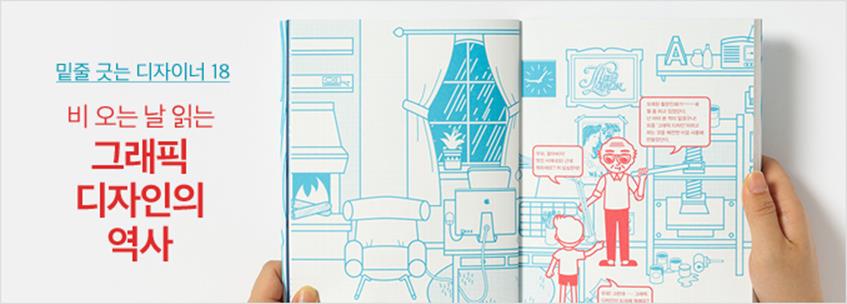
비 오는 날 할아버지 집에 놀러 갔다가 ‘그래픽 디자인이 뭐예요?’라는 질문에서 시작된 하룻밤의 디자인 역사 여행이 이 책의 큰 구조로 이루어져 있다. 산업혁명 초기에 이루어진 타이포그래피의 미약한 탄생부터 오늘날 인터넷을 중심으로 하는 글꼴의 유통까지.
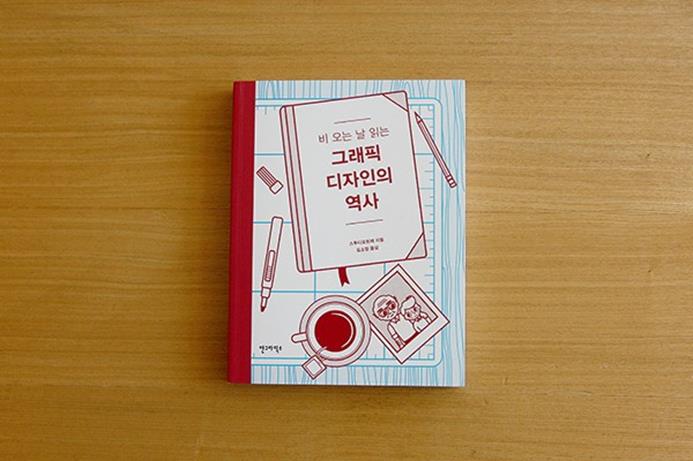
크리스마스카드를 처음 만든 사람은 누구일까?
다다의 이름은 어디에서 유래했을까?
최초로 CI를 만든 사람은 누구일까?
색상환은 누가 만들었을까?
푸투라, 유니버설, 길산스, 사봉 등 글꼴은 어떻게 만들어졌을까?
현재 우리가 쓰는 지하철 노선도의 형태를 가장 처음 만든 사람은 누구일까?
하룻밤의 디자인 역사 여행
페이지마다 두 가지 색상으로 이루어진 그래픽 일러스트레이션과 쉬워 보이는 화면구성에 이끌려 이번 기회에 머릿속에서 희미해진 디자인 역사를 가볍게 정리하자는 생각으로 이 책을 들었다.
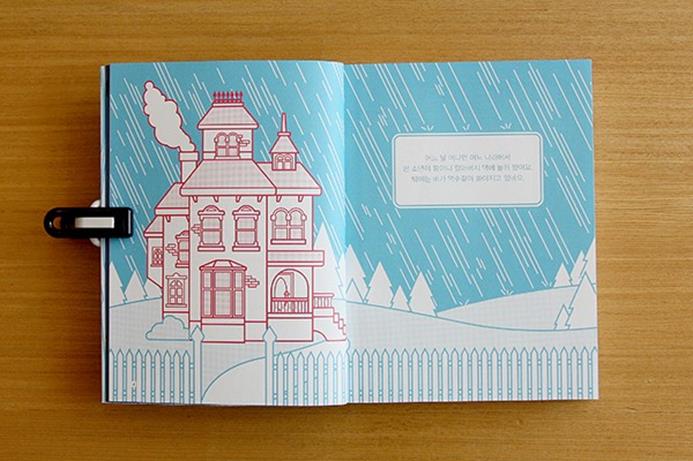
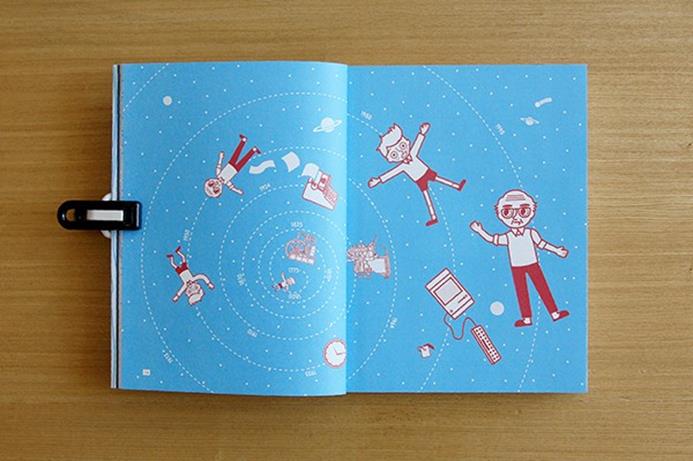
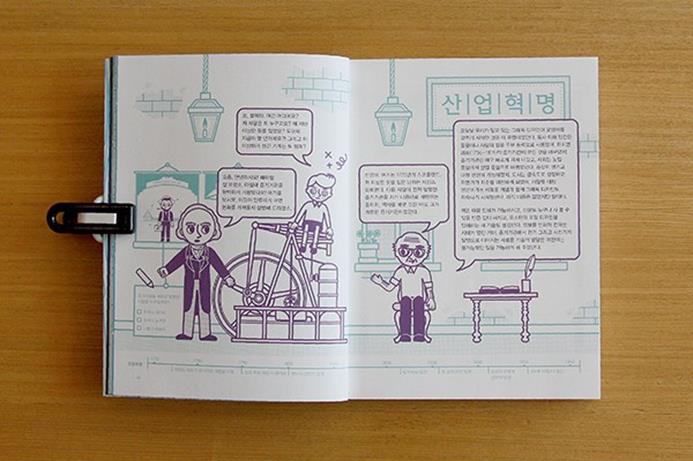
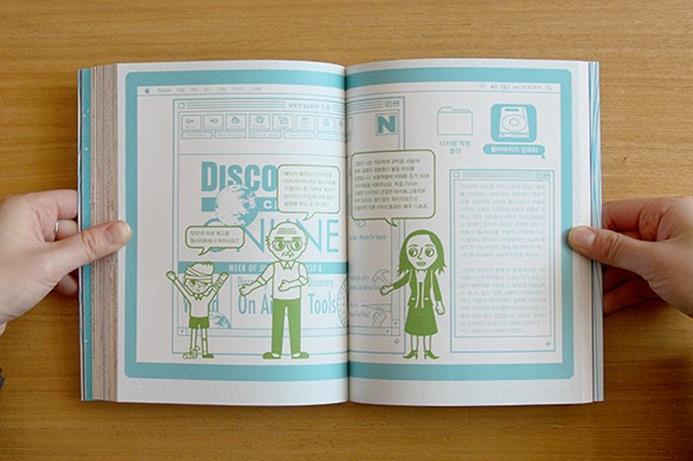
비 오는 날 할아버지 집에 놀러 갔다가 ‘그래픽 디자인이 뭐예요?’라는 질문에서 시작된 하룻밤의 디자인 역사 여행이 이 책의 큰 구조로 이루어져 있다. 산업혁명 초기에 이루어진 타이포그래피의 미약한 탄생부터 오늘날 인터넷을 중심으로 하는 글꼴의 유통까지. 아르누보, 미래주의, 다다 운동, 러시아 구성주의, 바우하우스 등 시대별, 연대별로 그래픽 디자인의 특징을 일별하며 그래픽 디자인 세계에서 일어난 굵직한 사건들과 오언 존스, 알폰스 무하, 윌리엄 브래들리, 앙리 반 데 벨데, 엘 리시츠키 등 쟁쟁한 대가들을 찾아간다. 그 과정에서 그래픽 디자인과 관련된 궁금증을 하나둘씩 풀어낸다.
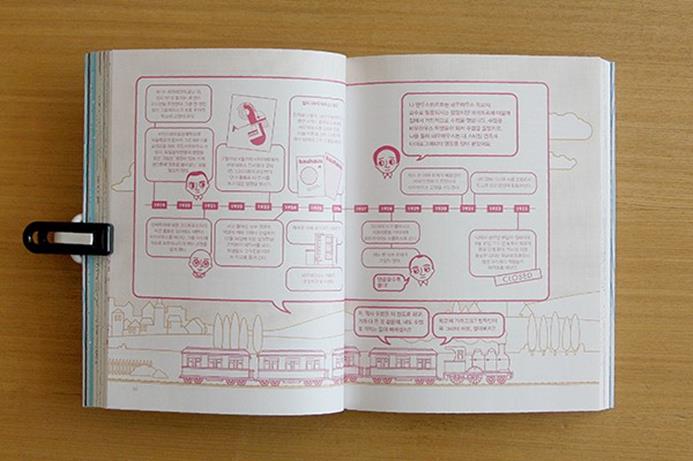
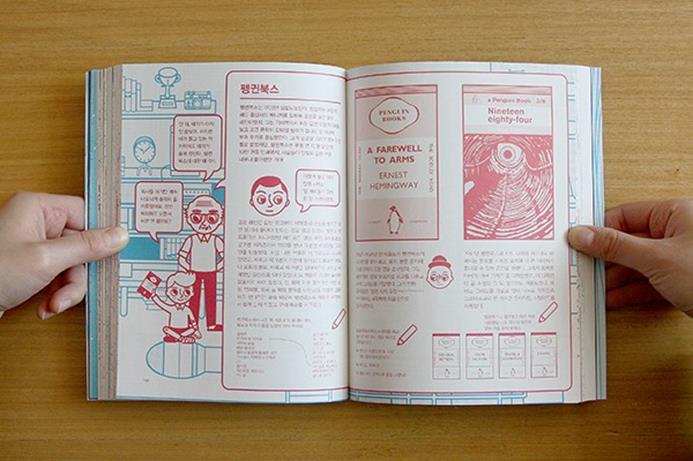
신문과 잡지부터 책 표지, 상품 라벨, 포장지, 각종 글꼴이나 기업체 로고, 포스터, 음반 재킷,웹사이트, 심지어 영화 타이틀 시퀀스까지.
그래픽 디자인의 역사의 사건과 그 시대에 굵직굵직한 역사의 흐름도 함께 알려주어 더 큰 흐름을 이해하는 데 도움을 준다.
P.78-79
바우하우스 1919-1933
-바우하우스라고 들어 오셨나요? 요즘엔 독일 어디를 가도 그 이름을 들을 수 있더군요. 그 학교에 피닝거라는 사람과 이야기를 나눠 보니 디자인이나 미술에 대해 나와 비슷한 생각을 하고 있더라고요. 바이마르에 바우하우스가 있는데, 그곳에서 가르치게 되기를 바라고 있습니다.
-그럼요, 들어봤지요. 디자인 전반, 특히 그래픽 디자인 분야에서는 짧지만 강렬한 흔적을 남긴 곳이니까요. 바우하우스의 철학을 형성하는 데 수많은 사람들이 힘을 보탰고 서로 다른 세 곳의 학교가 새로운 현대 디자인 운동의 중심이 되었지요. 또 바우하우스는 진정한 디자인 교육 환경을 만들려는 첫 시도이기도 했답니다.
-바우하우스의 학생들은 도예와 건축, 그리고 사진에 이르기까지 수많은 기술을 익혀야 했답니다. 오른쪽의 표는 학생들이 공부한 여러 과목을 잘 보여 주고 있지요. 바우하우스 교육 과정…생략
1918 – 제1차 세계대전 종전
1920 – 최초의 라디오 광고가 전파를 탐
1922 – 독일의 심각한 인플레이션
1924 – 유성 영화 발명
1926 – 레닌사망
1928 – BBC설립
1930 – 주가 폭락, 대공황
1932 – 엠파이어 스테이트 빌딩 완성
1934 – 아돌프 힘틀러가 독실 수상이 됨
1936 – 나치 독일에서 올림픽 개최
간단한 퀴즈와 직접 오릴 수 있는 부록까지 곁들여 디자인의 세계를 경험할 수 있도록 도왔다.
하지만 퀴즈의 답은 책에 포함되어있지 않고 다운받아야 한다. 그렇기에 찾아보는 재미가 있다.
흔히 볼 수 있는 교과서적인 디자인사 책만 봐왔던 나에게 사실 이 책은 조금은 불친절한 책이었으며, 어려웠다고 고백한다. 가볍게 읽으려고 생각했다가 퀴즈의 답을 찾기 위해 여러 번 검색해야 했으니 말이다. 하지만 찾아본 만큼 더 기억에 남는 장면들이 많았고, 우리가 날마다 접하는 물건들에서 그래픽 디자인이 어떻게 쓰이고 발전해왔는지에 대한 결코 짧지 않은 역사를 압축적으로 잘 알려주기에 이 책을 읽어보길 추천한다.